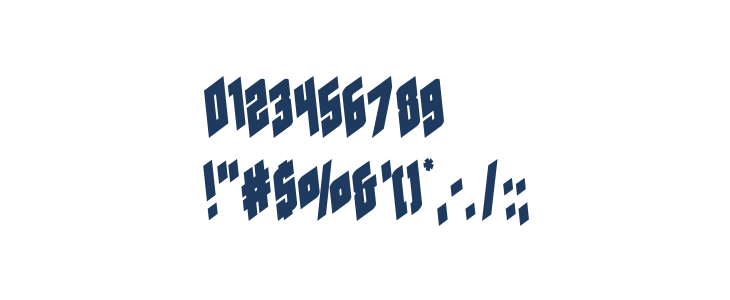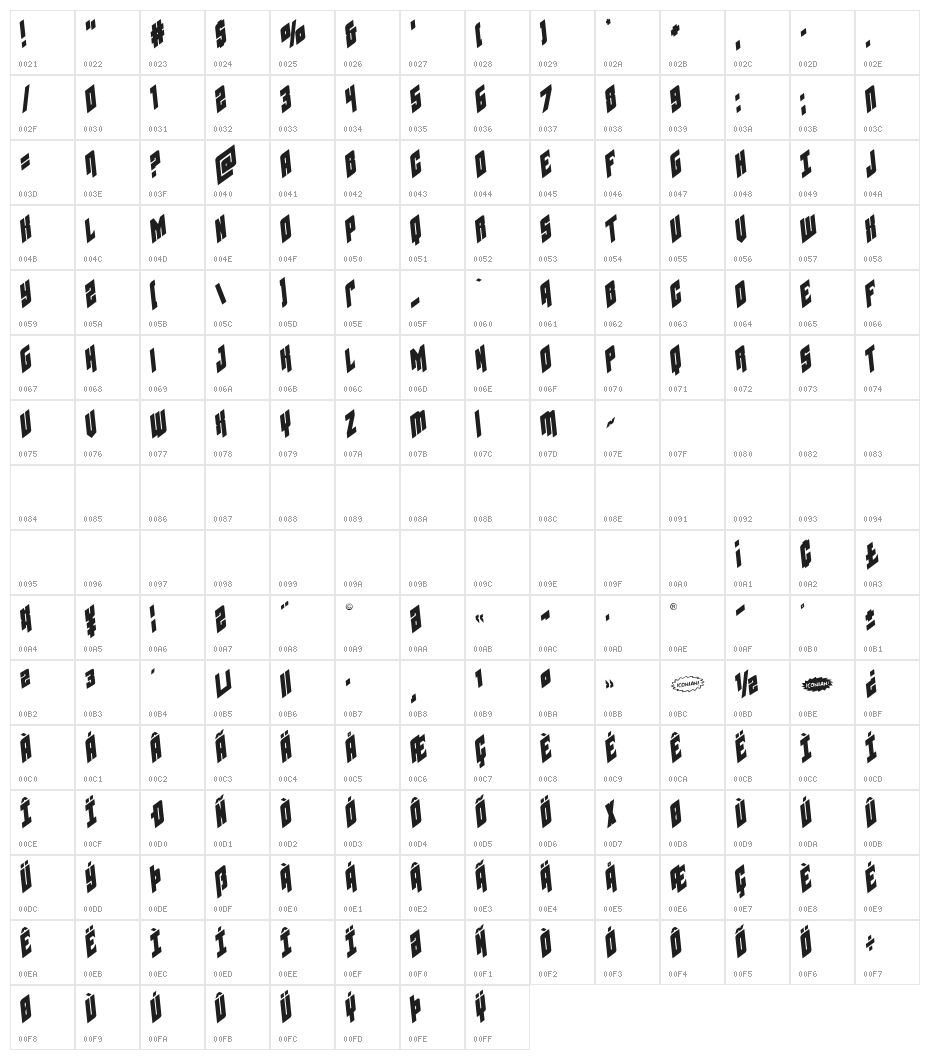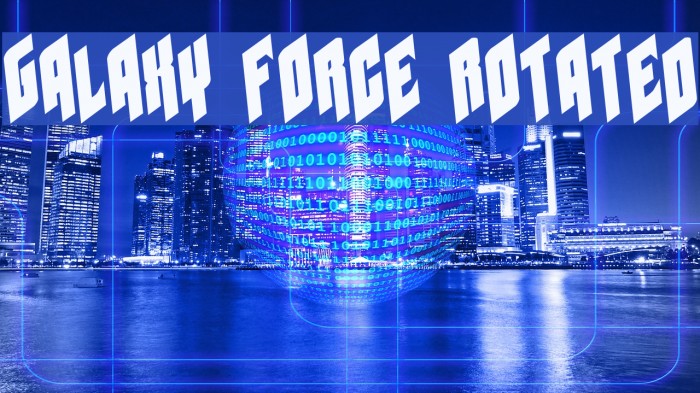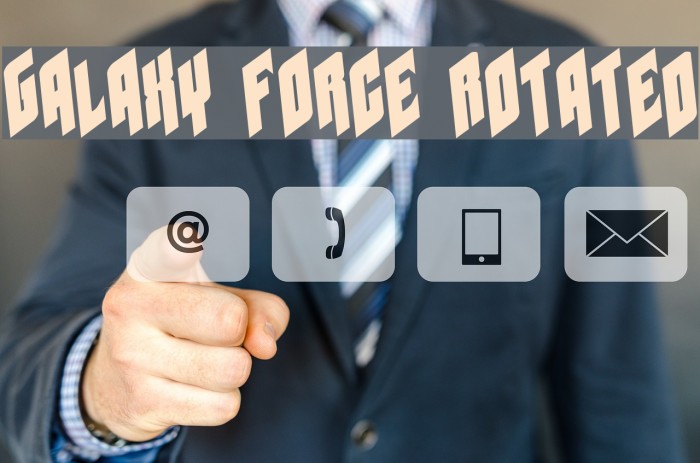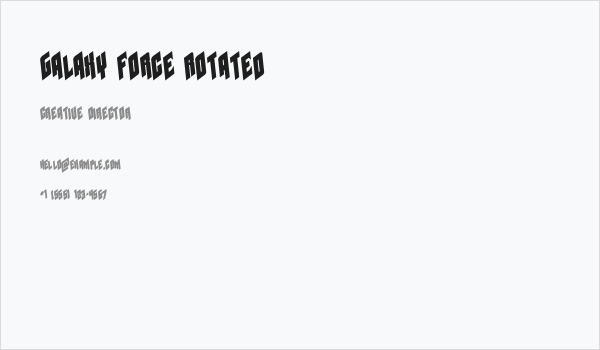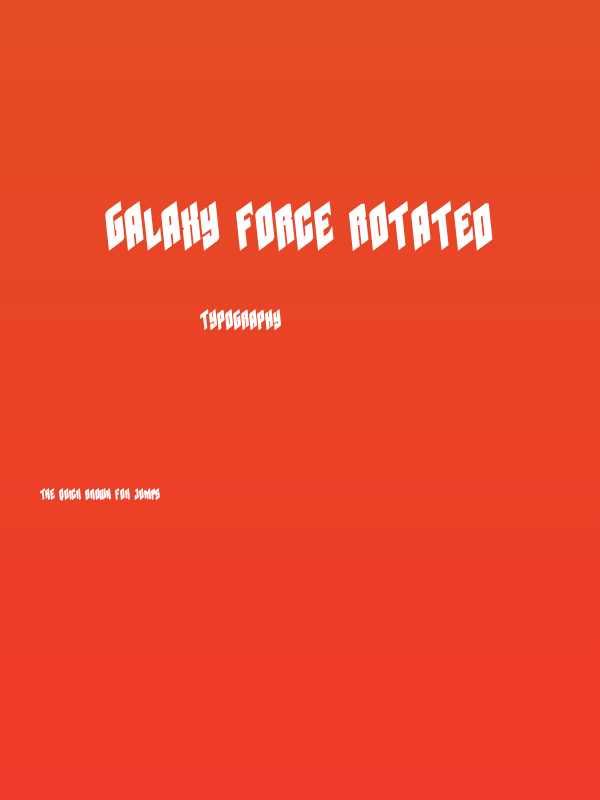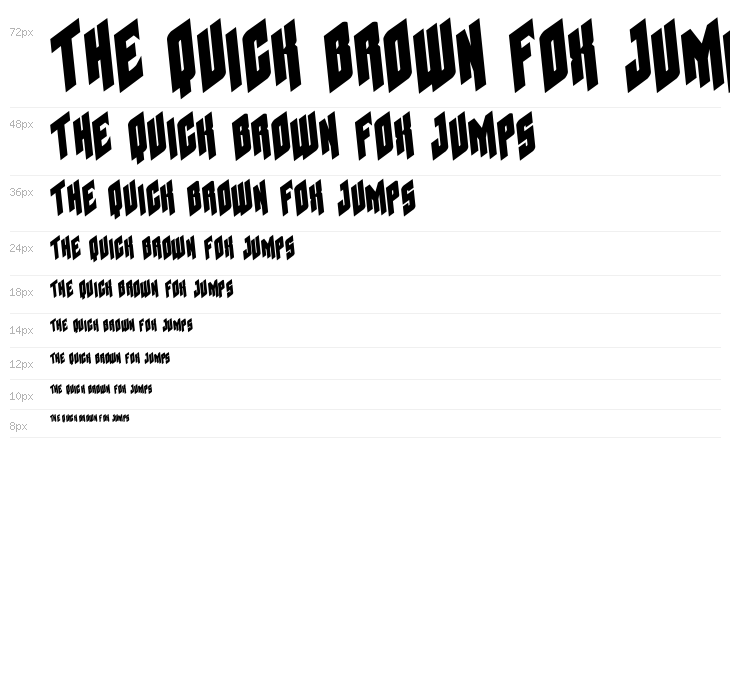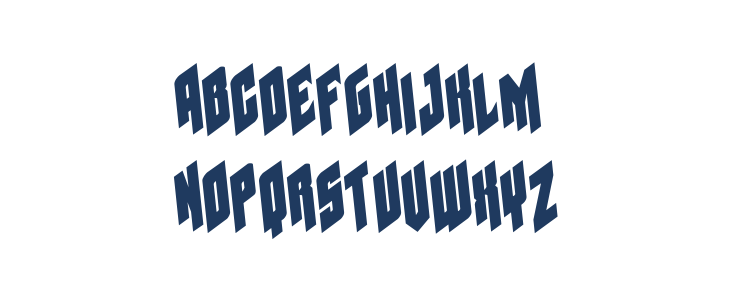
Galaxy Force Rotated Font
| Stile generale | Futuristic, Dynamic |
| Progetti proposti | Ideal for sci-fi themed designs, video game titles, posters, and branding that requires a strong, energetic presence. |